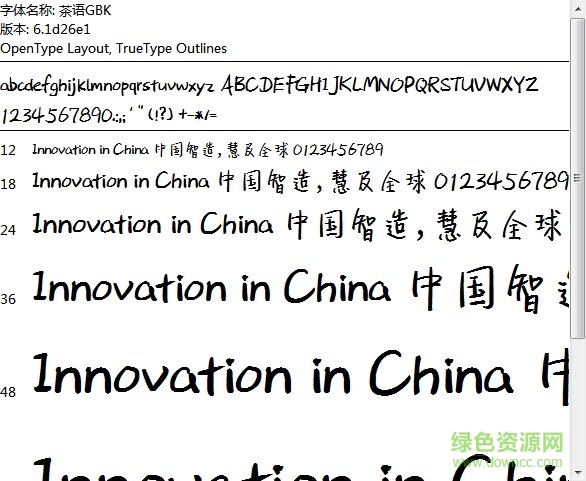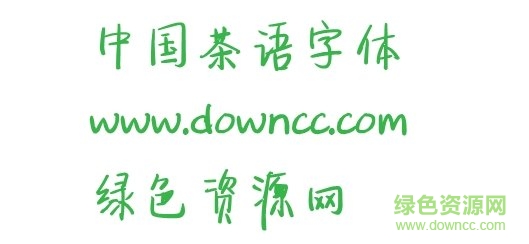
中國(guó)手寫茶語(yǔ)體ttf
中國(guó)茶語(yǔ)字體是一款書寫流暢、用筆溫婉的手寫字體,中文柔軟秀氣、英文工整簡(jiǎn)潔,是一款表達(dá)效果極佳的pop字體,很多網(wǎng)友都在找這款字體,綠色資源網(wǎng)特意分享出來(lái),歡迎下載哦!
中國(guó)茶語(yǔ)字體ttf特色
茶語(yǔ)字體,與新蒂下午茶字體比較香色,但在英文書寫上更具特色,打破了沉重的造型模板,更顯得字母的流暢與連貫性。
茶語(yǔ)字體純屬手工輸入,字形瀟灑大方,效果非常不錯(cuò),能夠應(yīng)用于簽名設(shè)計(jì)、平面設(shè)計(jì)、名片設(shè)計(jì)、廣告創(chuàng)意、印刷包裝等領(lǐng)域。